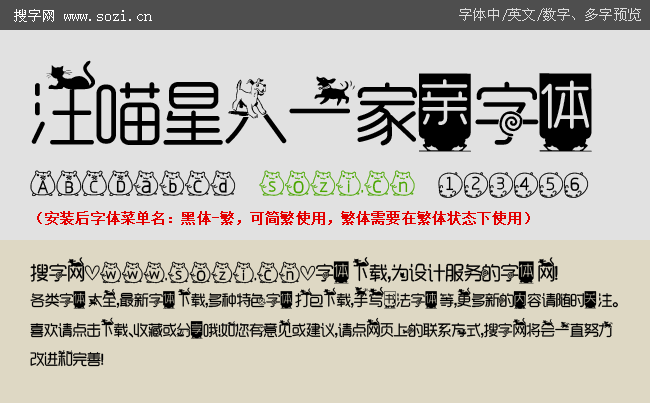
汪喵星人一家親字體
搜字網(wǎng)給大家提供一款很有趣的手機(jī)中文字體下載。字體名字叫汪喵星人一家親字體,這款手機(jī)字體是以造字工房悅黑體字體為原形,為字體插入了卡通圖案與邊框。即保持了悅黑體易識(shí)別的風(fēng)格,又增強(qiáng)了趣味性,特別適合喜歡手機(jī)字體個(gè)性一些的朋友在手機(jī)上安裝使用。